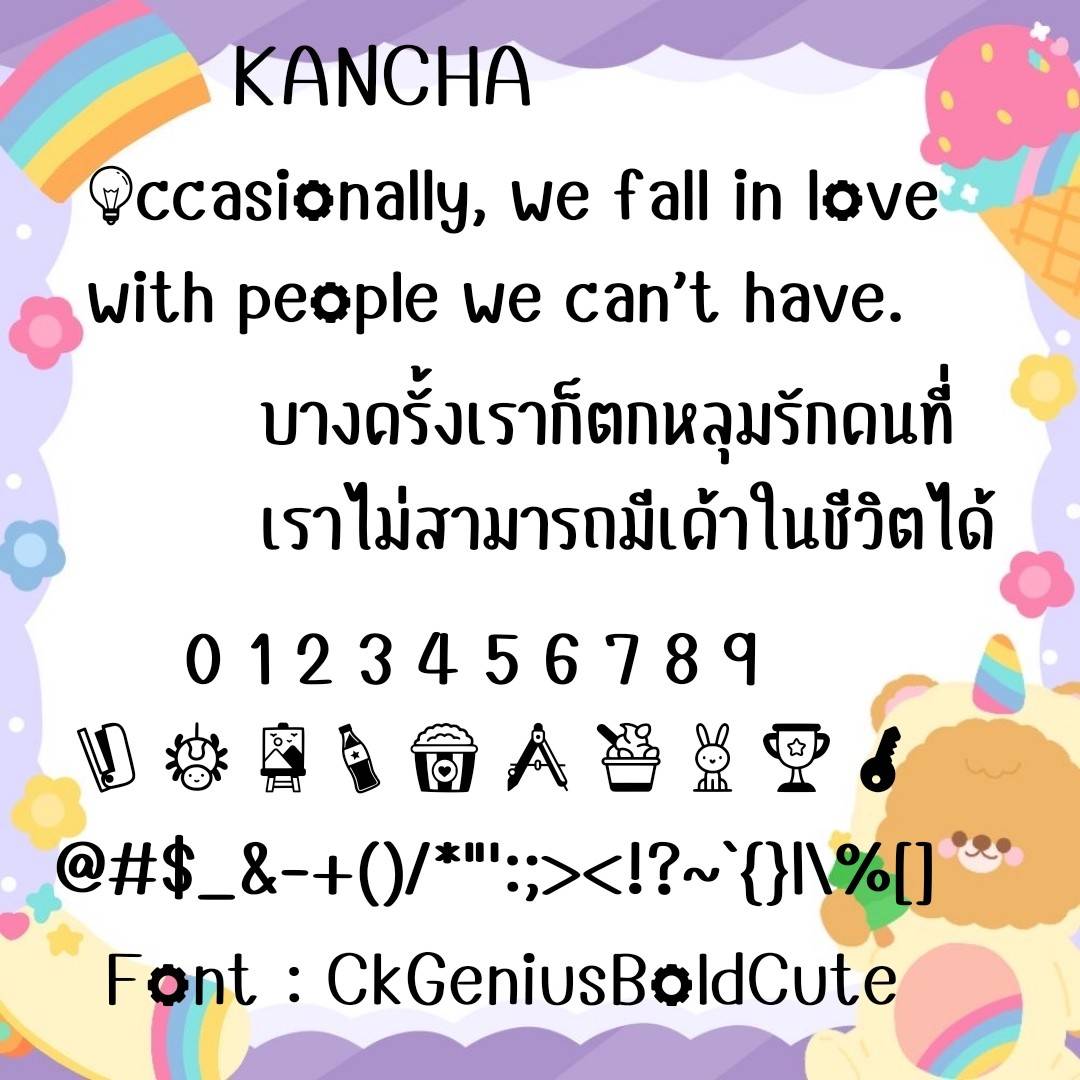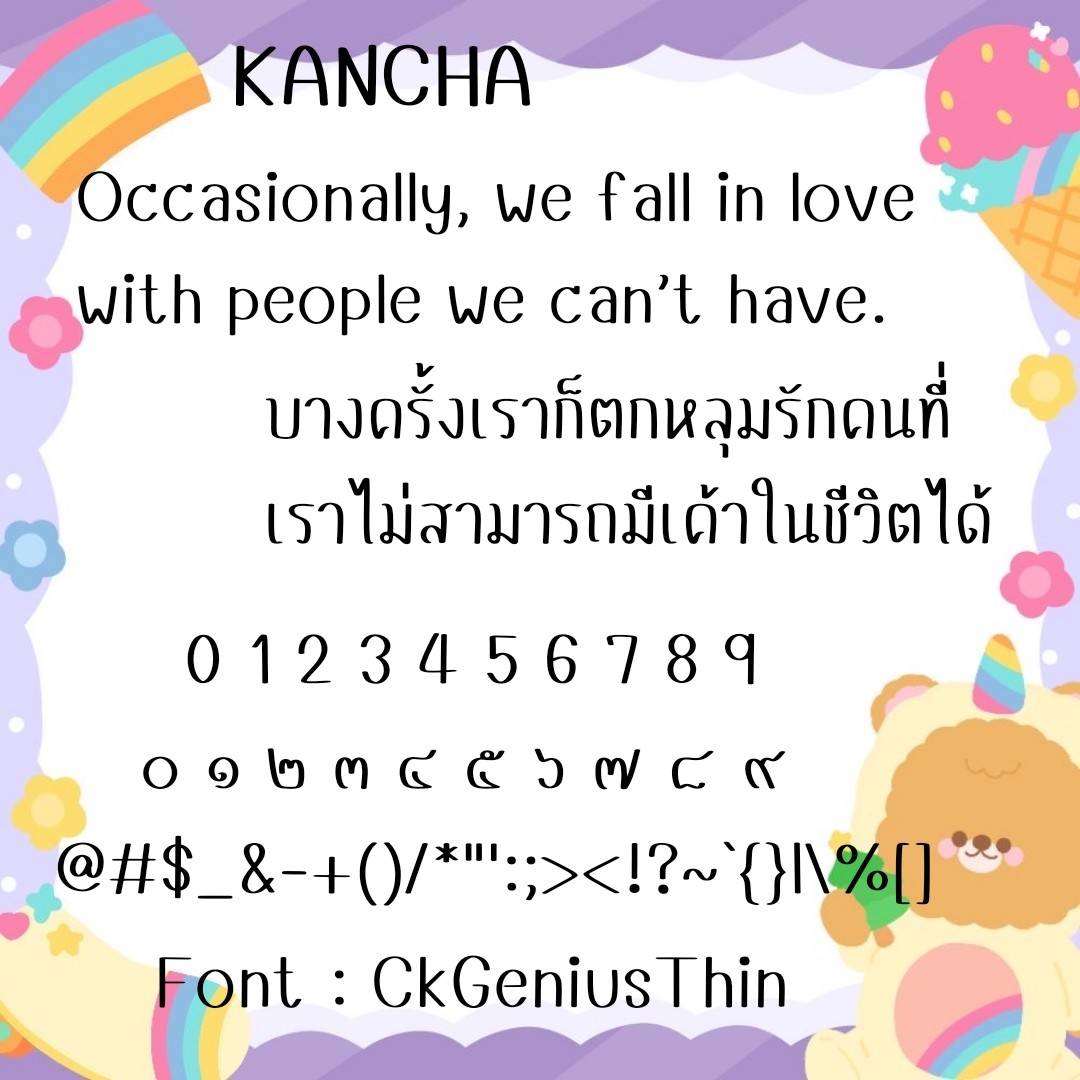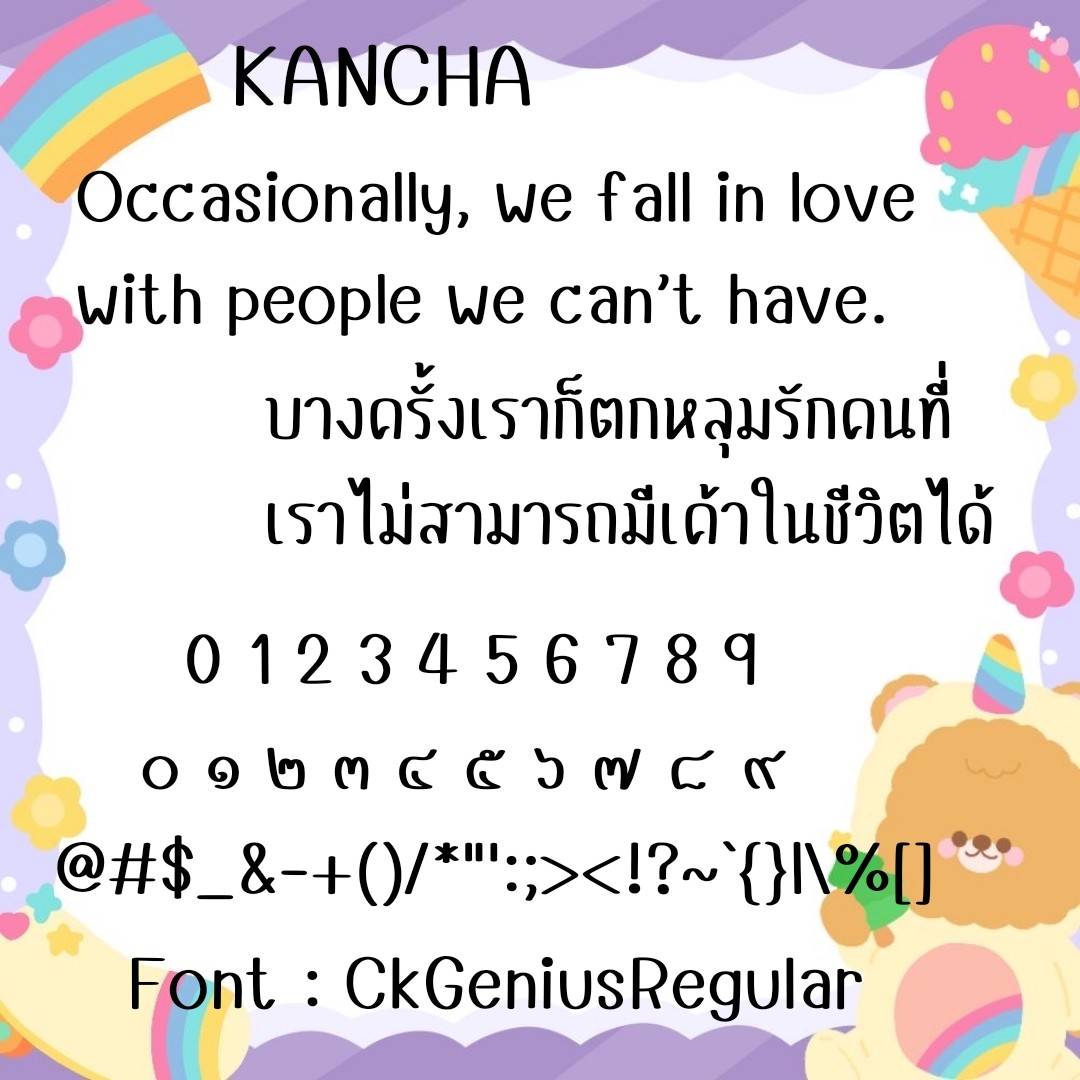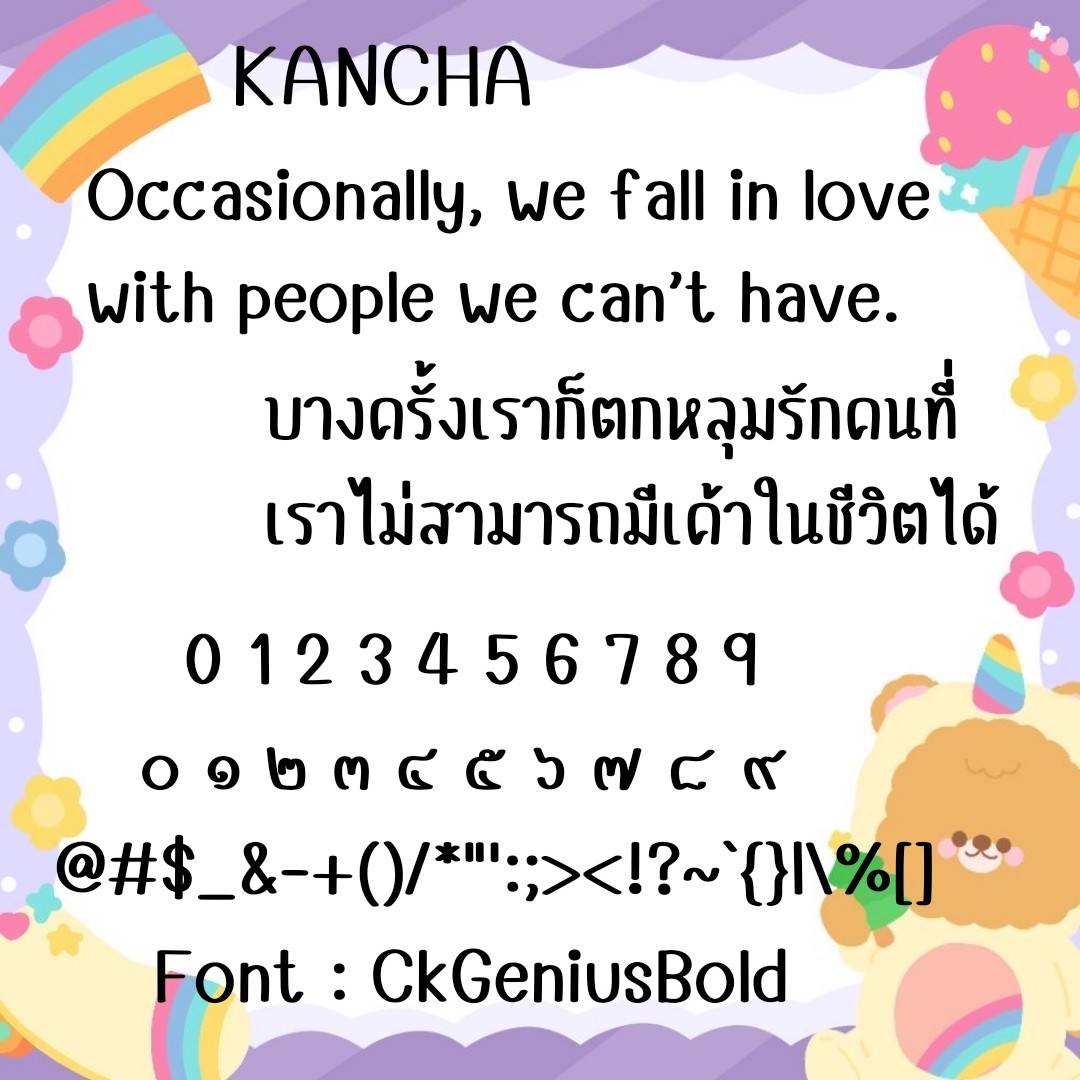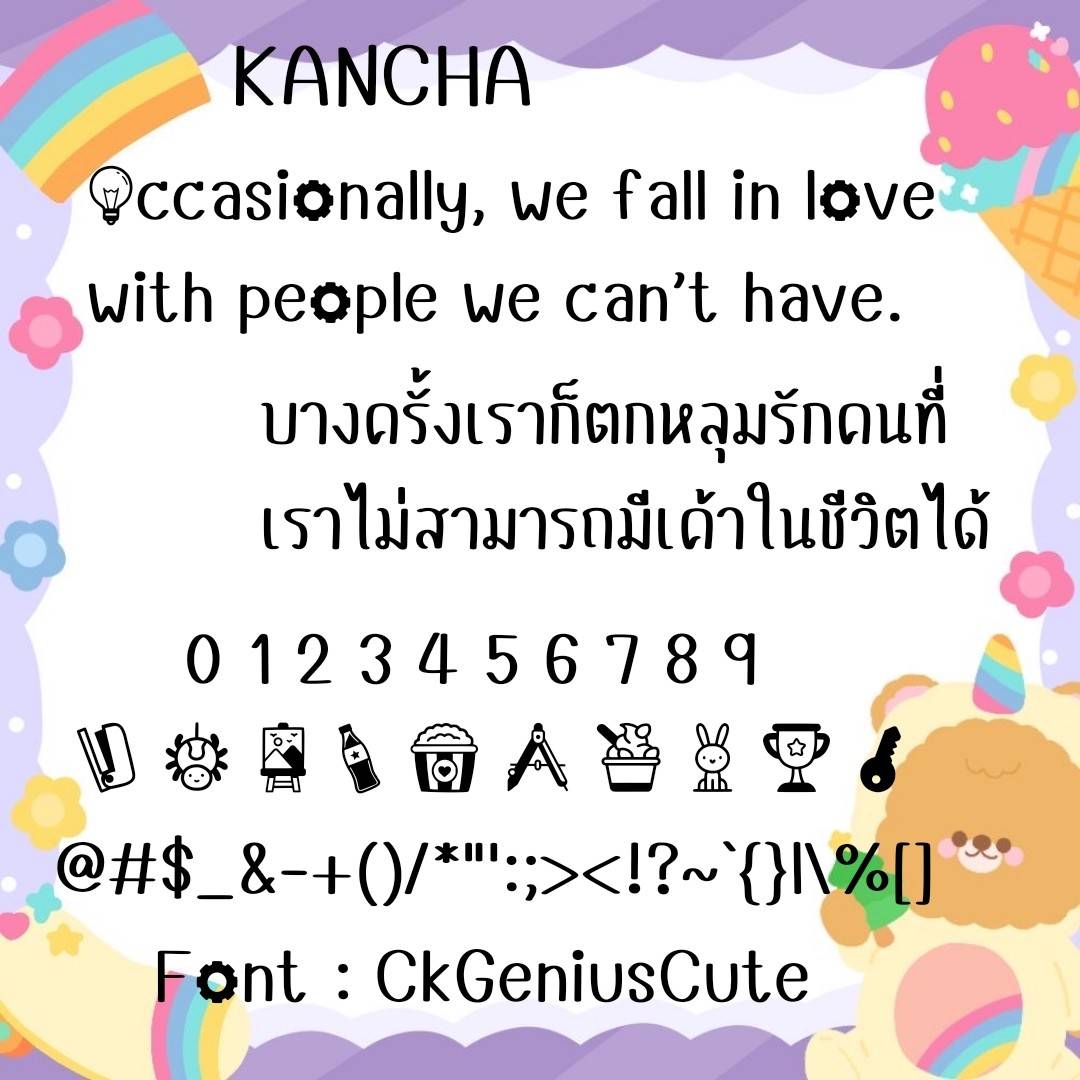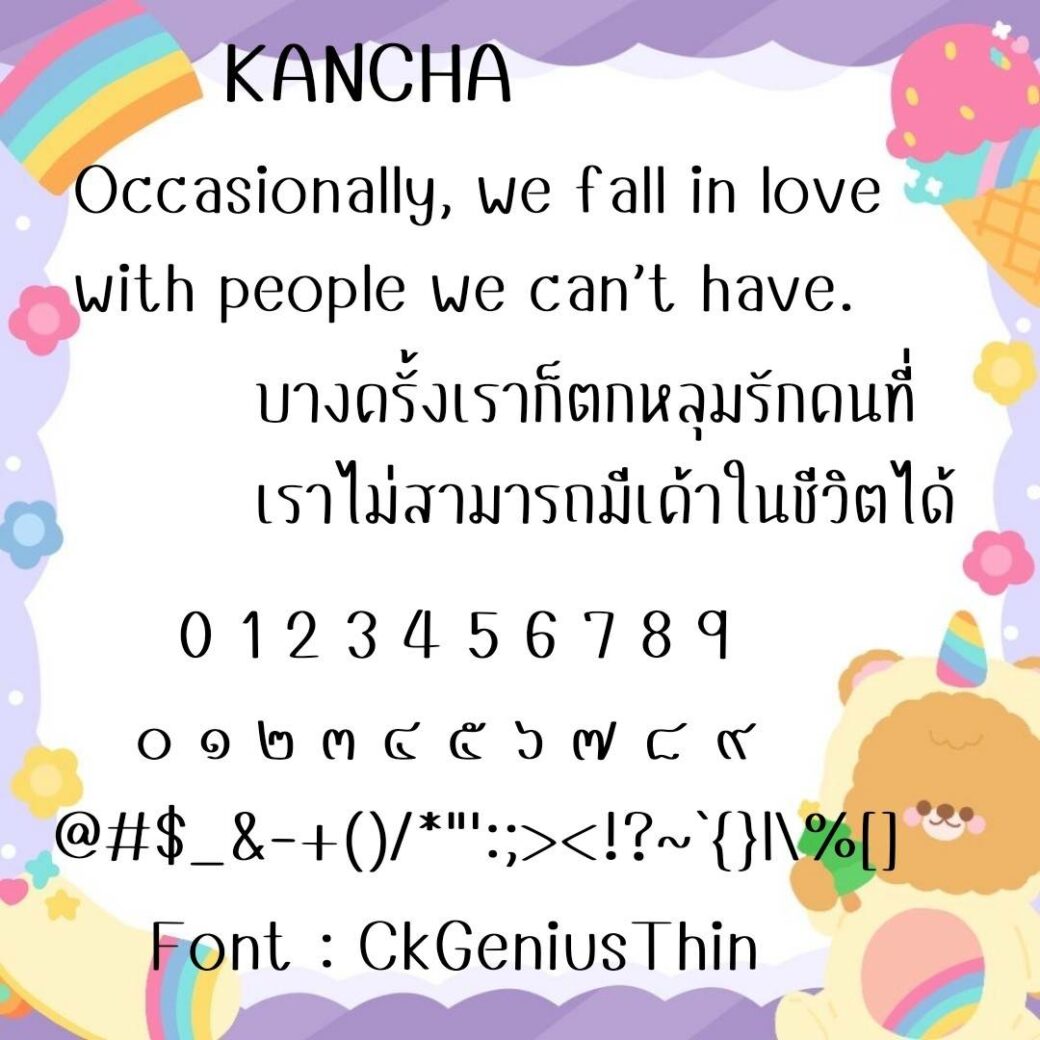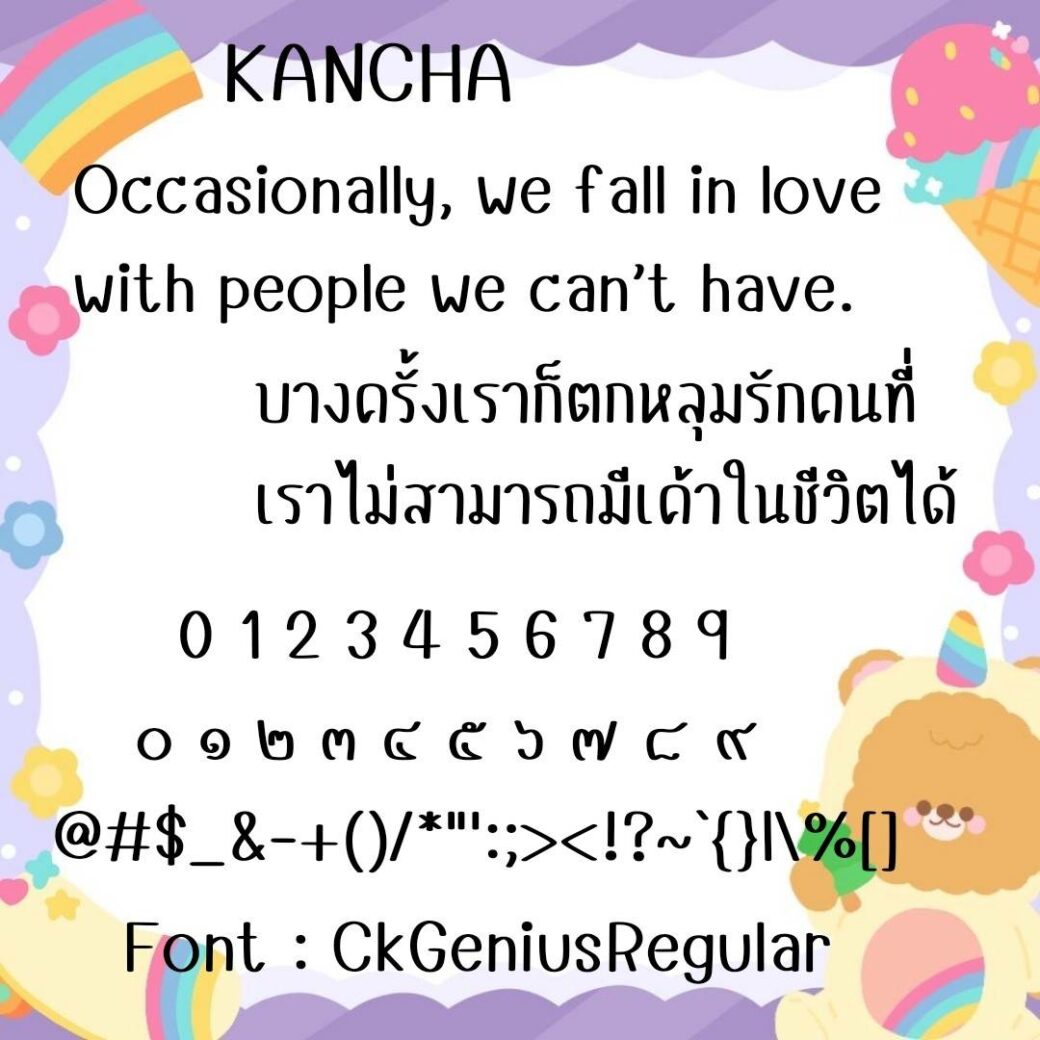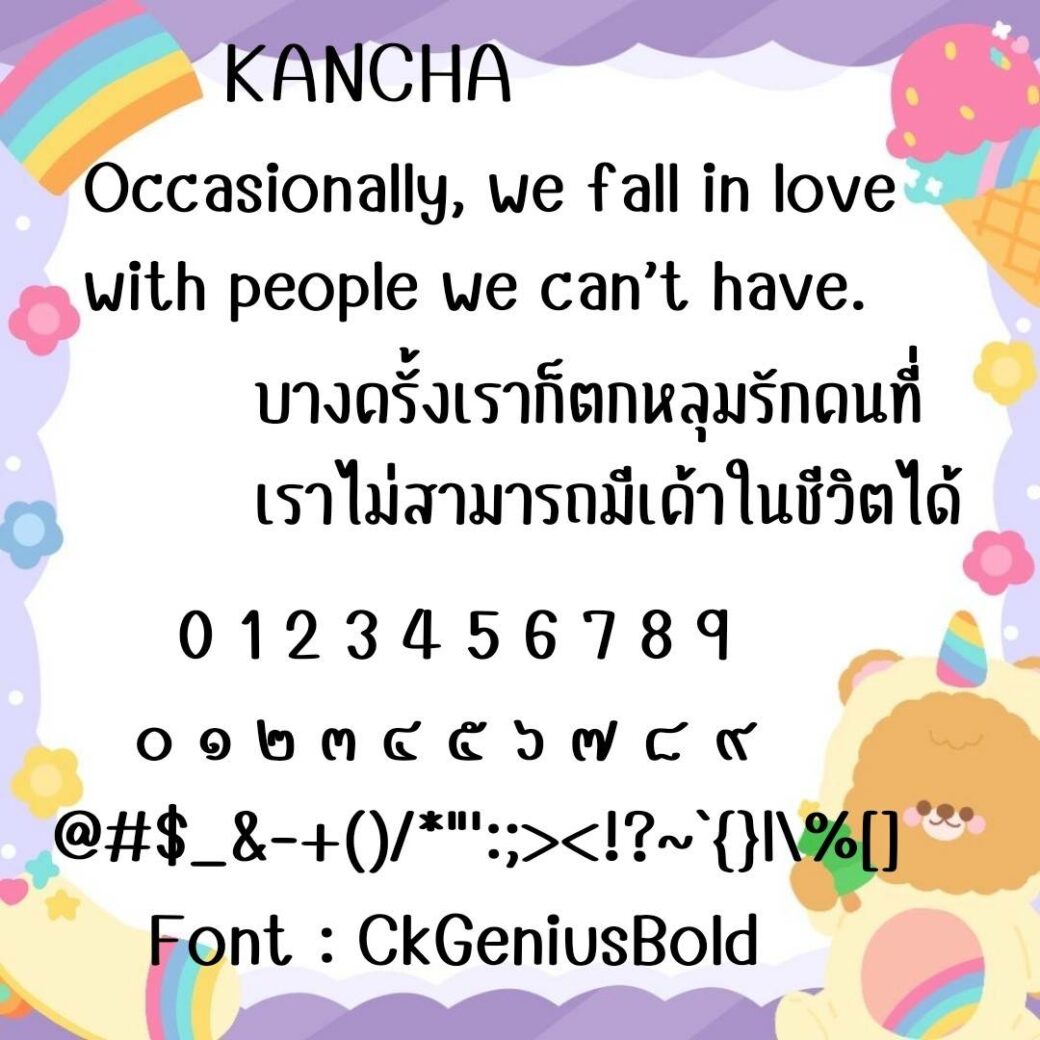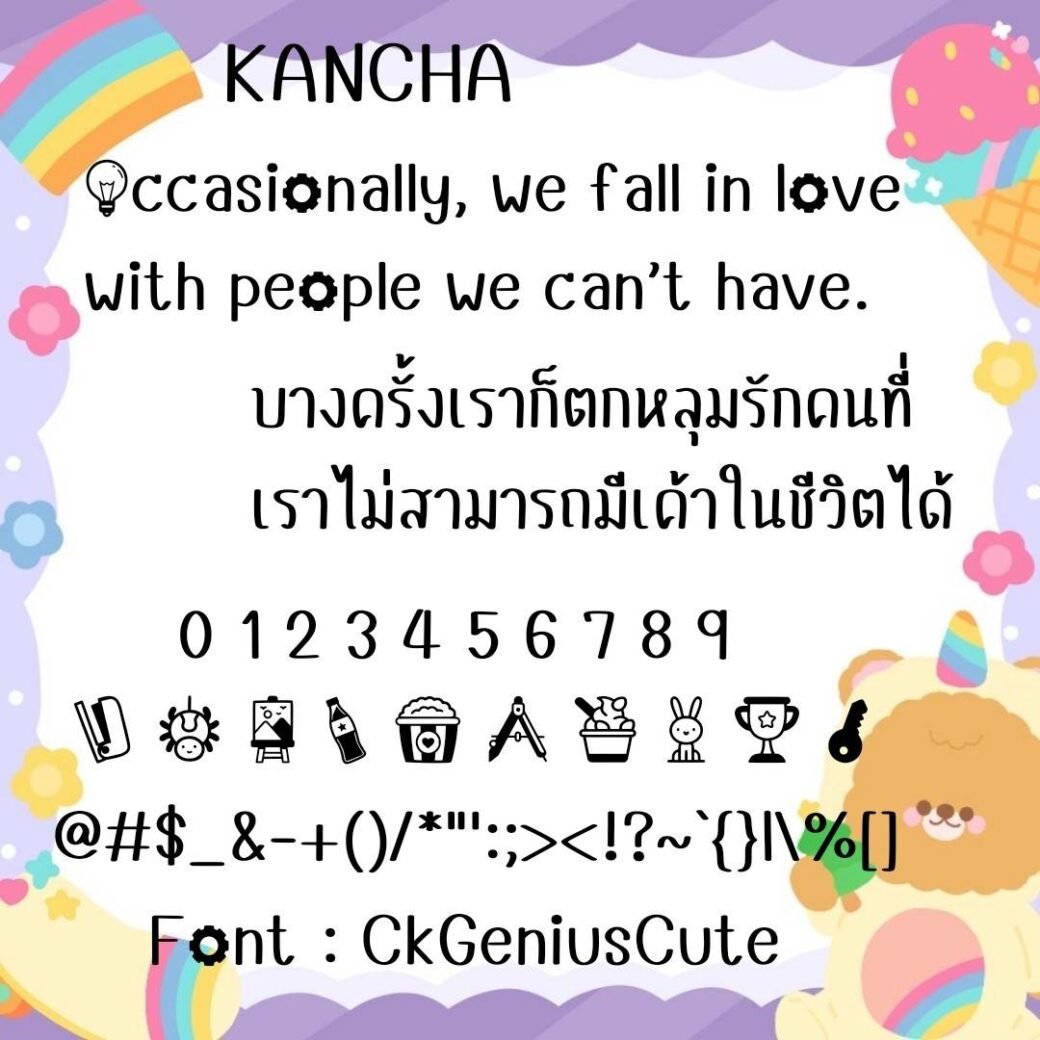
Font CkGenius
ชื่อสินค้า : Font CkGenius 💙
🔸ฟอนต์แนววัยรุ่นแนวไม่มีหัว ตัวพอดีๆ ไม่อ้วนไม่ผอมจนเกินไป มีความกึ่งเหลี่ยมนิดๆ และยังมีไฟล์อิโมจิน่ารักๆแทนเลขไทยให้ในชุดด้วยค่ะ 🥰💙
🔹Teenage style font, no head, just right body, not too fat, not too thin. It’s a bit semi-square. And there is also a cute emoji file instead of Thai numbers in the set as well🥰💙